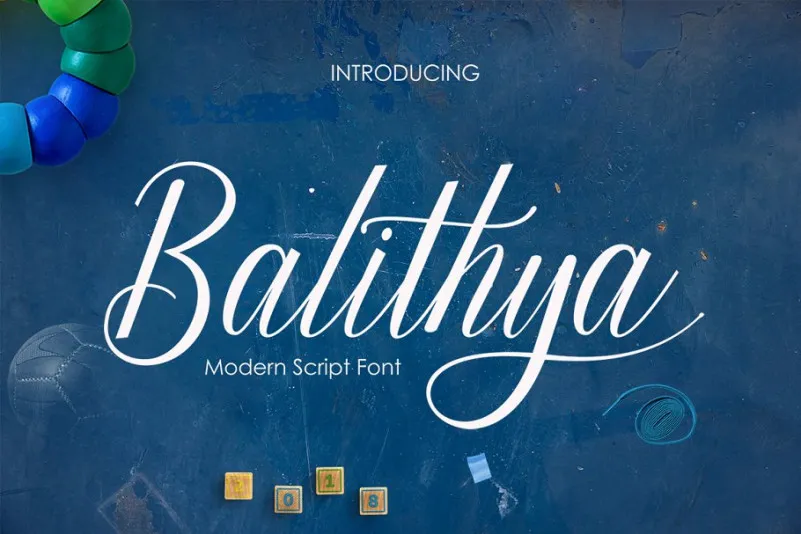
Balithya Calligraphy Font – Download Grátis
A Balithya Calligraphy Font é uma nova escolha para designers digitais entusiasmados com letras aquarelas e fluxos naturais. Desenhada pelo designer Hamilton, essa fonte é um lindo complemento para seus projetos mais recentes. Com sua graça elegante e suavidade natural, a Balithya Script oferece uma experiência visual única que combina elementos delicadamente elaborados com linhas de escrita fluidas. Ela é perfeita para aqueles que desejam incorporar um toque autêntico ao design de suas páginas, seja em editoriais pessoais ou trabalhos profissionais. Ideal tanto para designers digitais quanto para amantes da arte e do design gráfico, essa fonte permite uma personalização única, transmitindo elegância e sofisticação. Sua simplicidade não diminui sua força, ao contrário: ela acentua o cuidado meticuloso na sua criação. Com suas linhas delicadas e seu suave fluxo de letras, a Balithya Calligraphy Font oferece uma experiência visual única e autêntica para aqueles que buscam trazer um toque de artesanato ao design digital. E não se preocupe com qualquer dificuldade em usar – a Hamilton está sempre disponível para ajudar e fornecer orientações adicionais sobre como explorar todas as possibilidades dessa bela fonte.